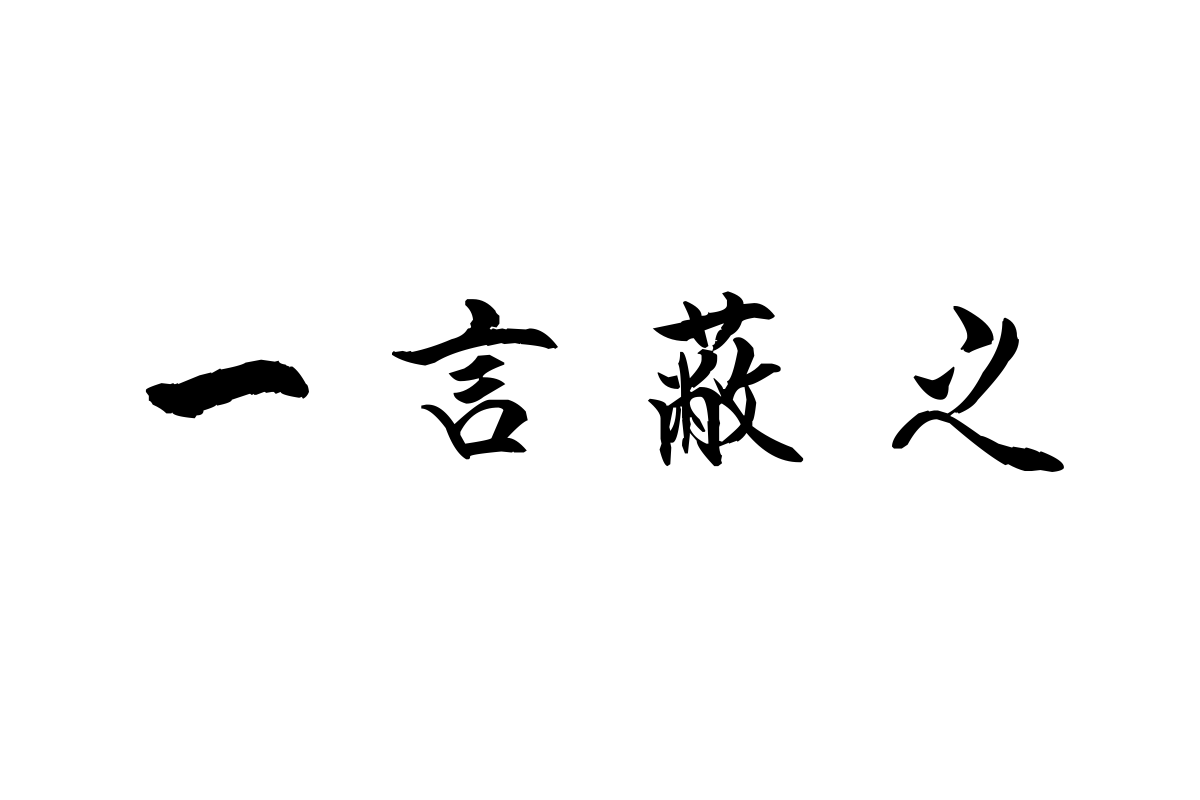
汉标串城体是一种新型的汉字字体,它的特点是将传统的汉字笔画和结构进行重新组合和设计,使得汉字更加美观、易读。这种字体的特点在于它的线条流畅、结构紧凑,给人一种简洁、明快的感觉。
汉标串城体的笔画粗细变化丰富,既有粗犷的线条,又有细腻的笔触,使得汉字在视觉上呈现出层次感。同时,汉标串城体还注重字与字之间的空间关系,使得整个字体看起来更加协调、平衡。
此外,汉标串城体还具有一定的装饰性,通过巧妙的设计,使得汉字在视觉上更加醒目,增加了汉字的艺术魅力。
总的来说,汉标串城体是一种既具有传统韵味又不失现代感的汉字字体,它为汉字的传播和展示提供了新的可能。